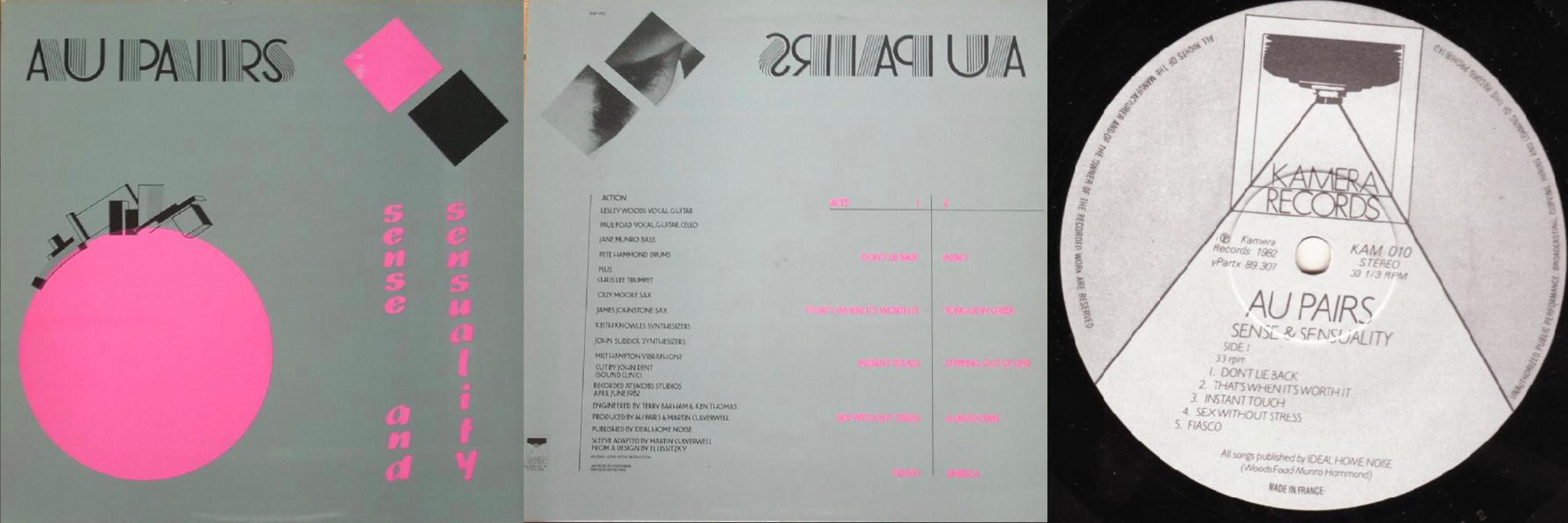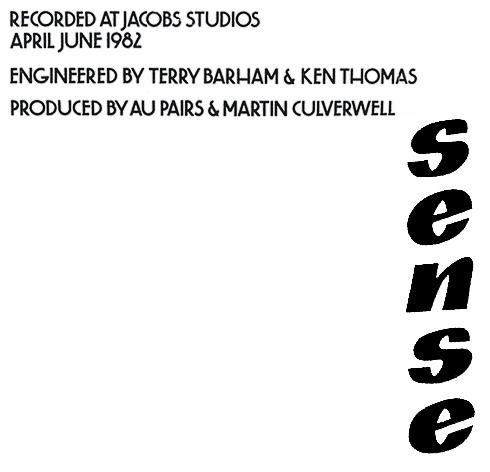
Suche diese 2 Fonts (s. Grafik) vom Layout des Albums "Au Pairs - sense and sensuality" 1982
Suche diese beiden Fonts (dürften auch etwas kosten). Sie stammen vom Cover des Albums "Au Pairs - sense and sensuality" von 1982.
Die Grafiken sind aus sehr schlechten Scans via Photoshop extrahiert. Ich denke, visuell vermitteln sie einen zumindest brauchbaren Eindruck. Die bisherige Websuche hat zu keinerlei Ergebnissen, auch was halbwegs ähnliche Fonts anbelangt, geführt. Wäre großartig, wenn hier jemand weiter wüßte, auch wenn ich mittlerweile nicht mehr allzuviel Hoffnung habe.
das Eine ist so eine typische Art-Deco-Schrift. Da fällt mir die Mostra Nova ein. Beachte die vielen alternativen Buchstabenformen:
Bei der anderen Schrift fehlt mir total der Anknüpfungspunkt zur Suche ... Kaffee ist leer und ich bin müde ...